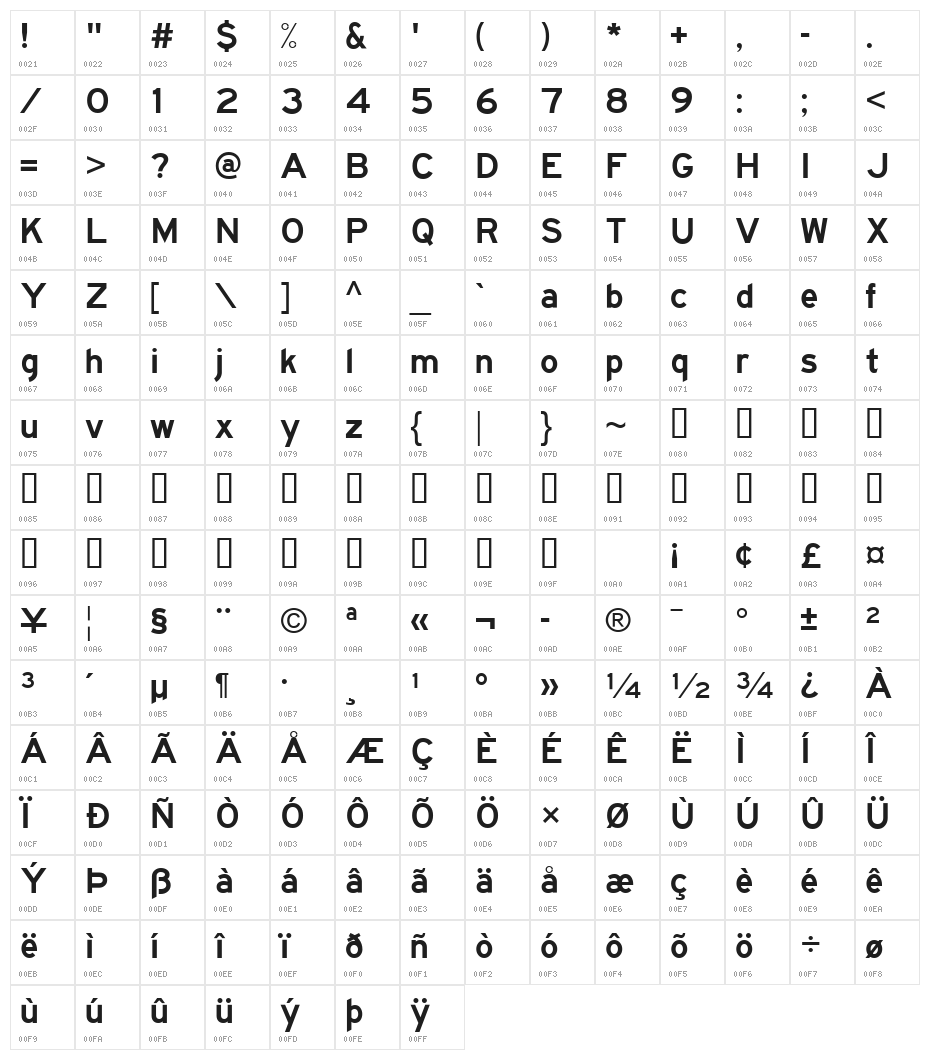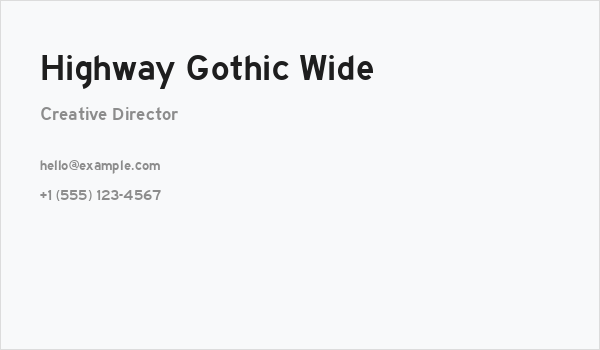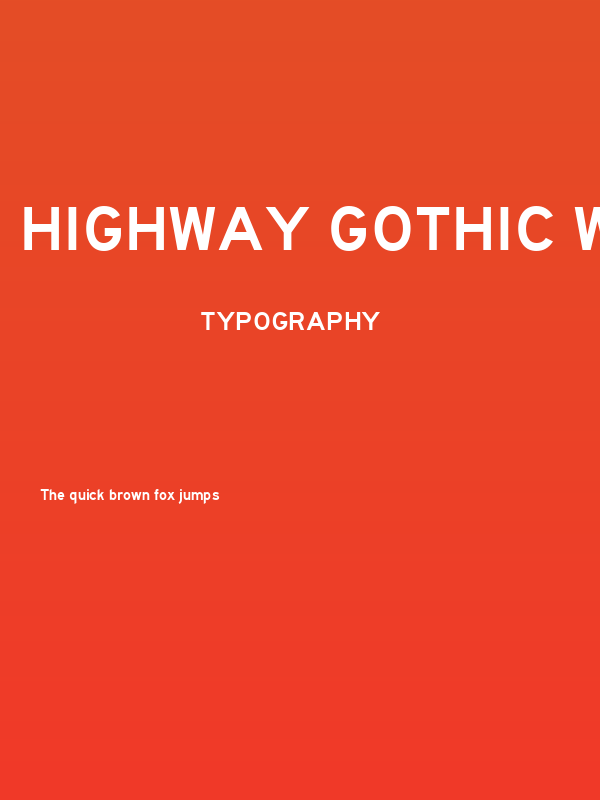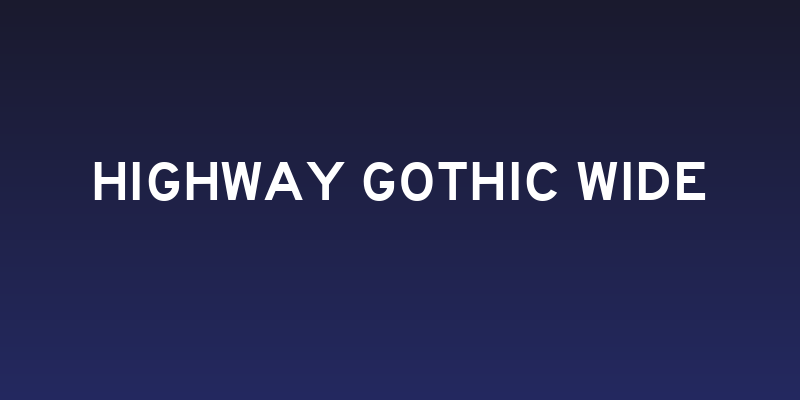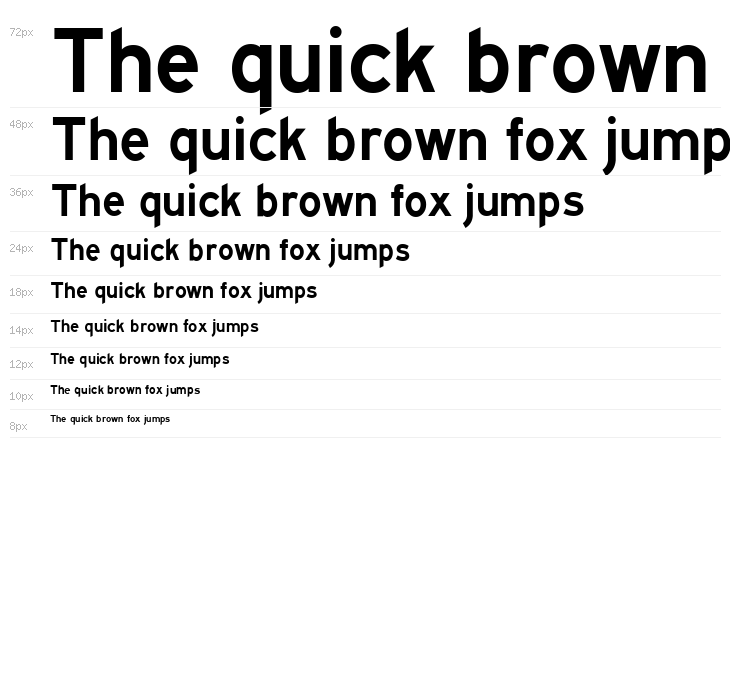
Highway Gothic Wide Font
| Breite | Expanded |
| Anwendungsfall | Headlines, Signage, Display |
| Vorgeschlagene Projekte | Ideal for highway signage, billboards, and other large-scale displays where readability from a distance is crucial. |